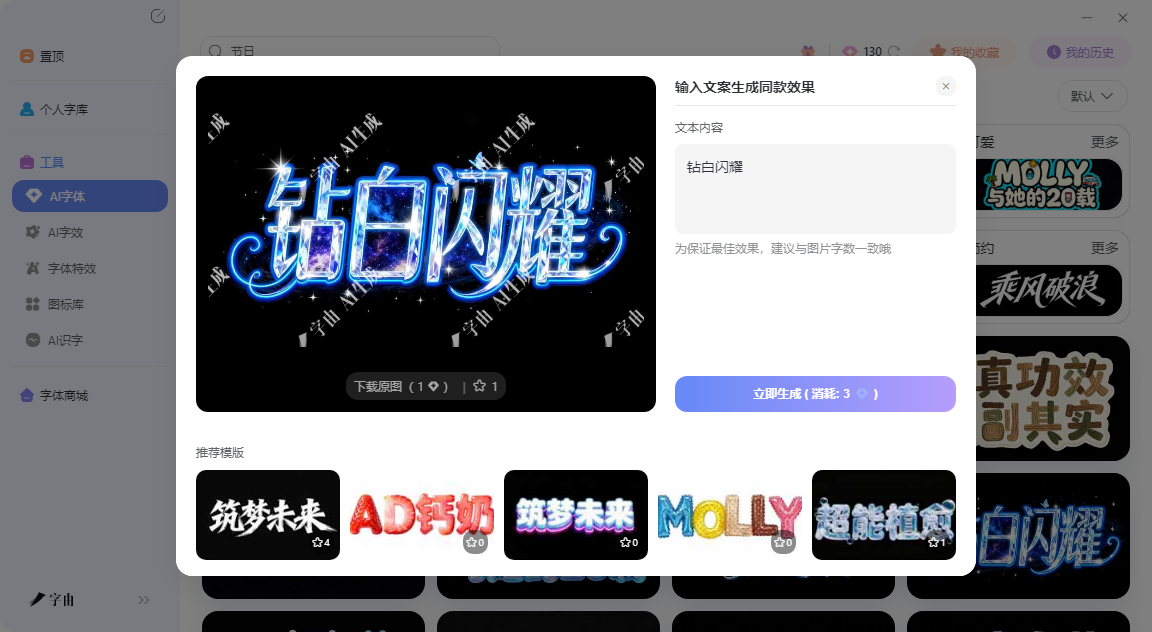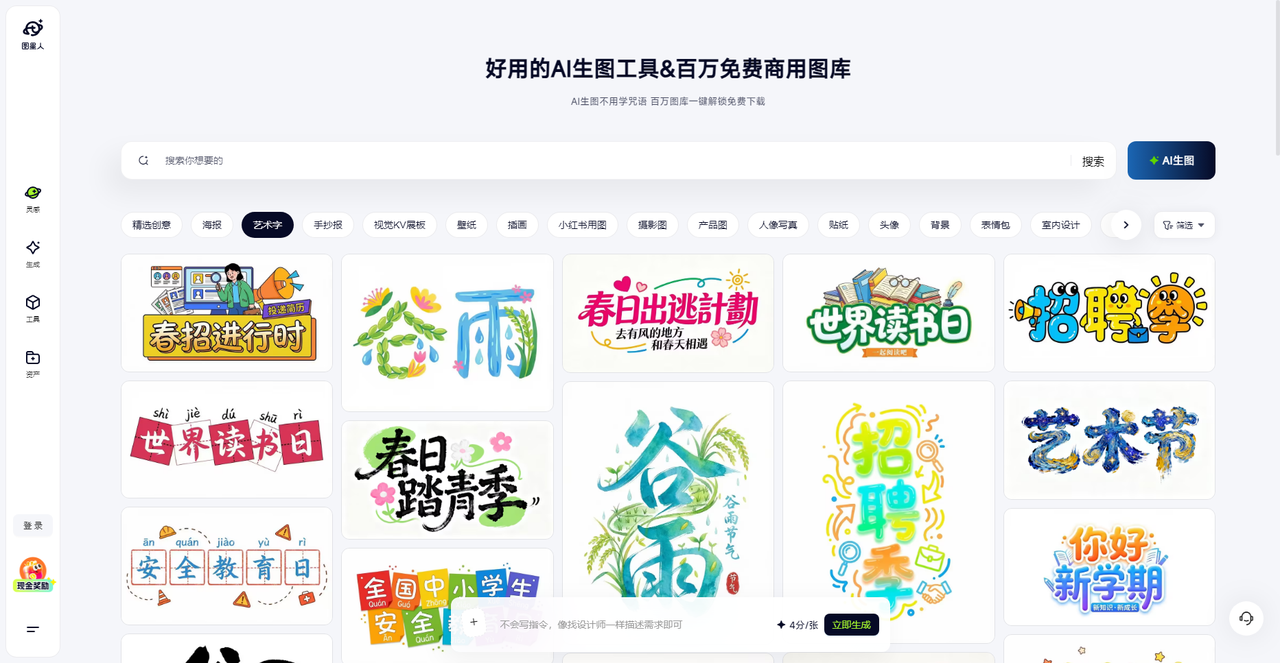
还在手动调字体?创意艺术字体在线设计神器推荐看这篇
你有没有过这种经历:做一张海报,文案定好了,排版也差不多,但标题那几个字怎么弄都觉得土。打开PS,从第一个字体试到最后一个,不是太死板就是太花哨。想加点特效,内阴影、外发光、渐变叠加调了半天,出来的效果还不如不调。其实创意艺术字体在线设计这件事只需要用一个轻量级工具就可以解决。现在市面上有不少在线工具,输入文字,选个风格,几秒钟就能出一张能用的艺术字图。今天实测了5款,从专业级到轻量级都有,看看哪个适合你。
先聊字由。很多人知道字由是因为它能管理字体,但它的AI字体功能,本质上是一个“创意艺术字体在线设计”的加速器。它不是让你从零开始设计,而是给你400多套现成的创意方案。字由的AI字体模板库,按风格和场景分得非常细。打开客户端,进入“AI工具”下的“AI字体”,左侧筛选栏里有“国潮风”“霓虹灯”“金属质感”“手写书法”“电商促销”“科技感”“文艺风”等十几个大类。每个大类下面又有几十款具体模板。
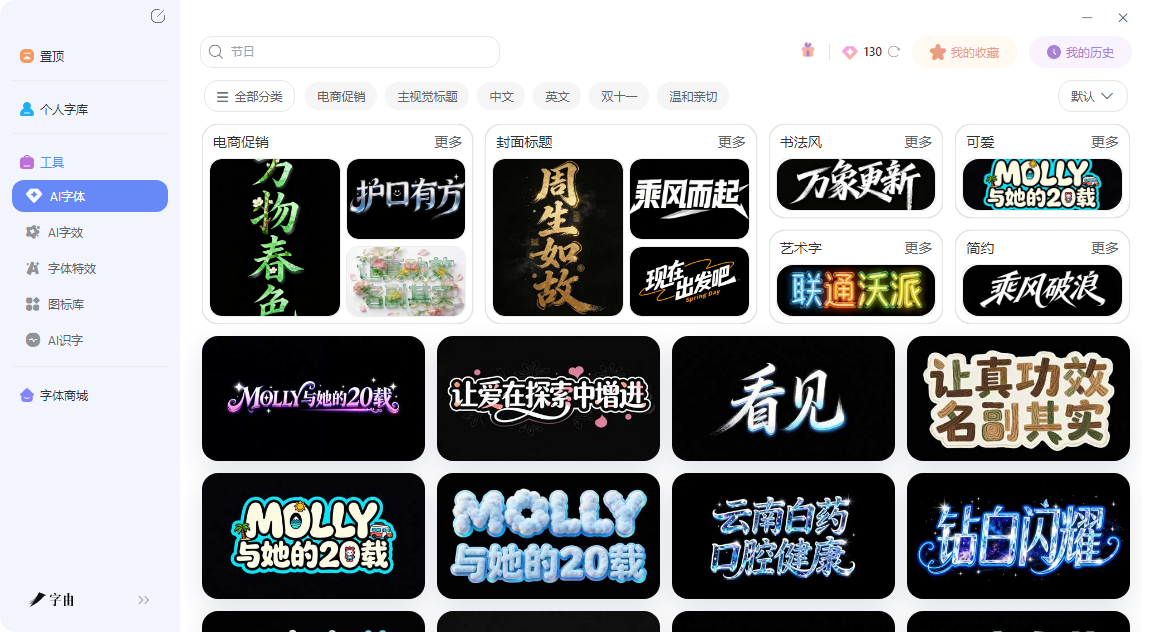
在字由,创意不是凭空想象,是在现成方案上做选择。很多人对“创意设计”有误解,觉得一定要从零开始才叫创意。其实专业设计师的工作方式也是“先找参考,再改”。字由的AI字体就是把“找参考”这一步提前帮你做了——400多套模板,每套都是专业设计师做的字体特效方案。你不需要自己调参数,只需要判断“这个风格适不适合我的项目”。
字由比较适合以下三类人使用:第一,电商运营。每天要出促销海报、详情页、主图,用“电商促销”分类里的模板,改几个字就能用,比等美工排队快多了。第二,自媒体创作者。封面标题需要抓眼球,字由的国潮风、霓虹灯模板比你自己在PS里调快十倍。第三,完全不懂设计的新手。不需要知道什么字体配什么效果,选模板、输文字、下载,三步完事。
2、图星人
第二个工具是图星人。截图显示它是一个综合性的AI生图和素材平台,首页有“AI生图”“灵感”“精选创意”“海报”“艺术字”“手抄报”“壁纸”“插画”等多个分类。它的“艺术字”板块应该是专门做创意艺术字体的。图星人的特点是“全”——它不只是一个字体工具,而是一个素材库。你可以在上面找灵感,看别人做的艺术字效果,然后自己生成。首页还展示了“春招进行时”“春日出逃计划”“世界读书日”“踏青季”“谷雨节气”等主题模板,每个主题下面应该都有对应的艺术字样式。如果你是自媒体运营,需要根据节日、节气快速产出带标题的封面图,图星人的主题模板可以节省很多找灵感的时间。
3、携飞工具
第三个工具是携飞工具,这是一个在线字体转换器,提供了大量的中文字体供用户选择。输入文字后,可以从“黑体、宋体、圆体、楷体、书法体、手写体、卡通体、复古体、创意字体、英文字体”等多个分类中选一款字体,然后调节像素大小、颜色、背景是否透明,点击“生成”就能得到艺术字图片。携飞工具的优势是字体多、操作简单。你不需要注册,不需要调复杂参数,选字体、打字、生成,三步搞定。适合那些“我已经知道要什么字体,只是想快速生成一张图”的用户。
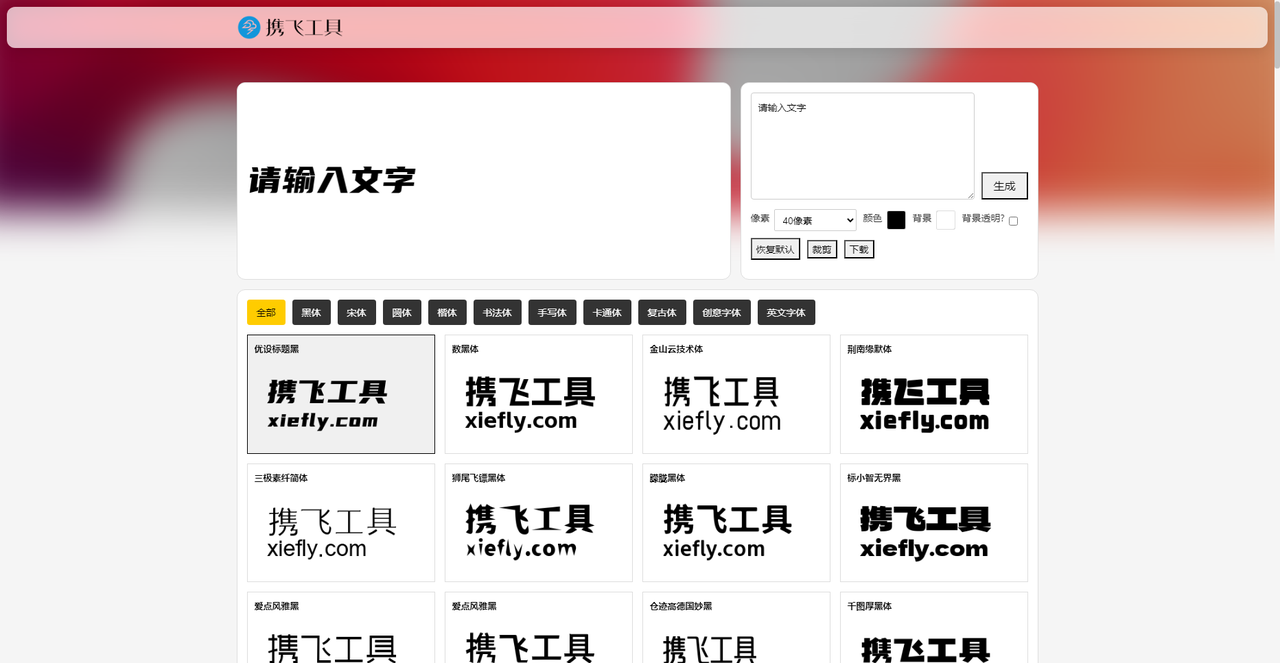
4、艺学网
第四个工具是艺学网。它的“艺术字体在线生成控制台”,支持倒影、投影、渐变等特效调节。输入文字后,可以选择字体(比如“叶根卡通”),设置字体颜色、上色、背景色、字体大小,然后打开或关闭“字体倒影”“字体渐变”“字体投影”,点击生成就能看到效果。和前面几个工具相比,艺学网给了用户更多的控制权。你不是只能从固定的模板里选,而是可以自己组合特效。比如你想要一个有倒影效果的艺术字,勾选“字体倒影”;想要渐变颜色,勾选“字体渐变”;想要阴影,勾选“字体投影”。这些特效可以叠加使用,自由度比纯模板工具高。
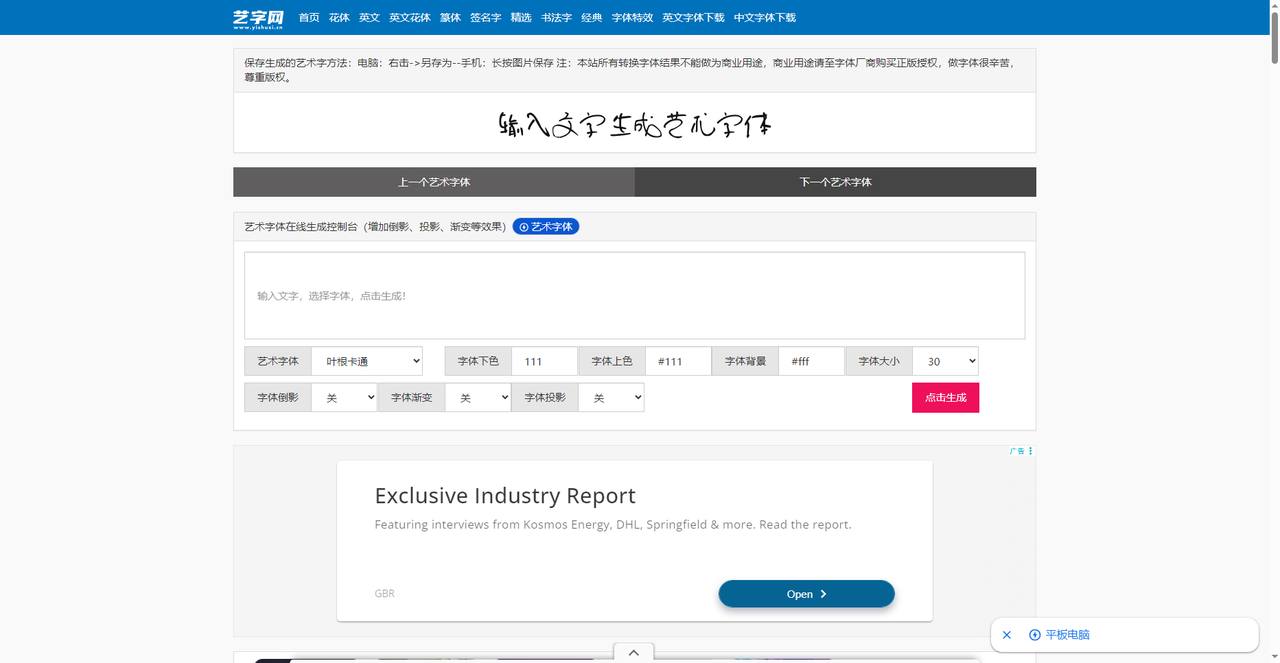
5、美术字
第五个工具是美术字。截图显示它是一个功能非常全面的在线文字特效编辑工具。打开页面后,你可以选择字体(默认、艺术字体、花体字体、POP体、毛笔字体、手写字体、篆书字体等),调节字体大小、颜色、背景宽度、背景高度、背景透明、填充纹理、背景纹理、背景颜色、渐变方向、横向间距、纵向间距等参数。还支持加粗、倾斜、下划线、中划线、左对齐、右对齐、竖排、翻转、复制、删除、渐变、加色等操作。可以添加多个文本图层,导入素材,使用特效模板。
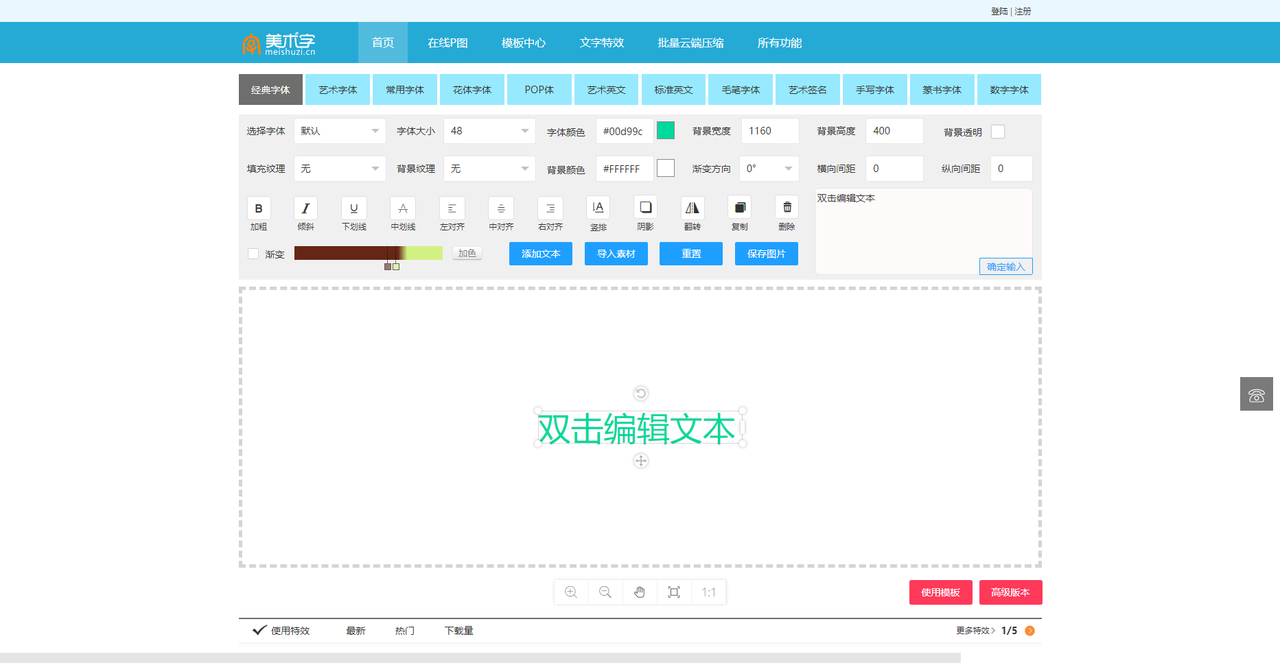
做创意艺术字体,工具没有高下之分,只有合不合适。如果你是一个赶时间的电商运营,字由的AI模板最省事,400多种风格选一个改文字就行。5个工具,5个定位。不用纠结哪个“最好”,看你现在手头是什么项目、还剩多少时间、对效果的要求有多高。打开网页试一下,输入你的文字,相信你几分钟就能够找到顺手的那个。